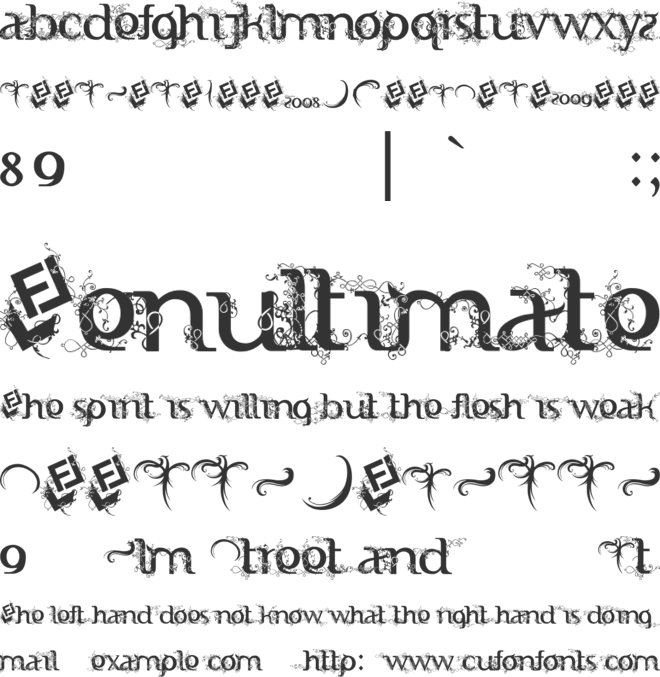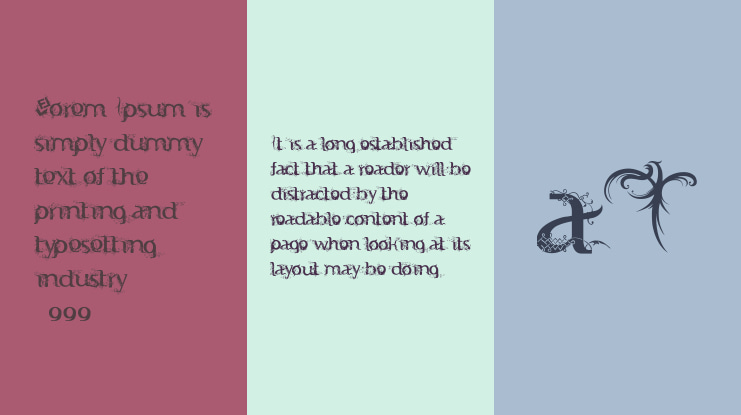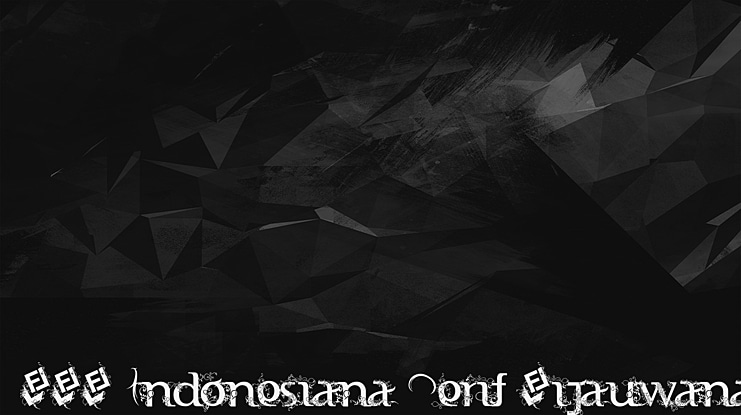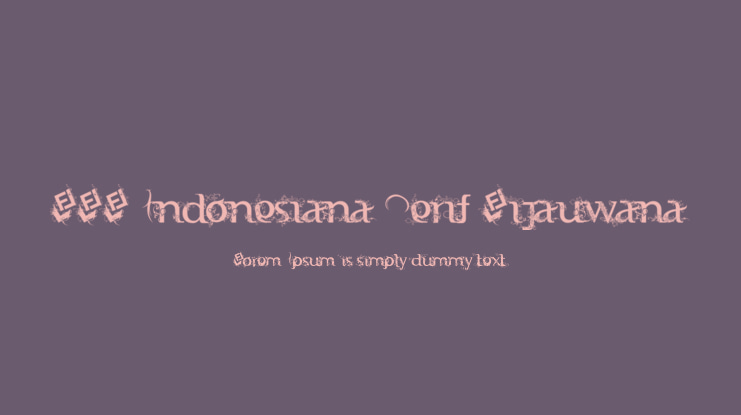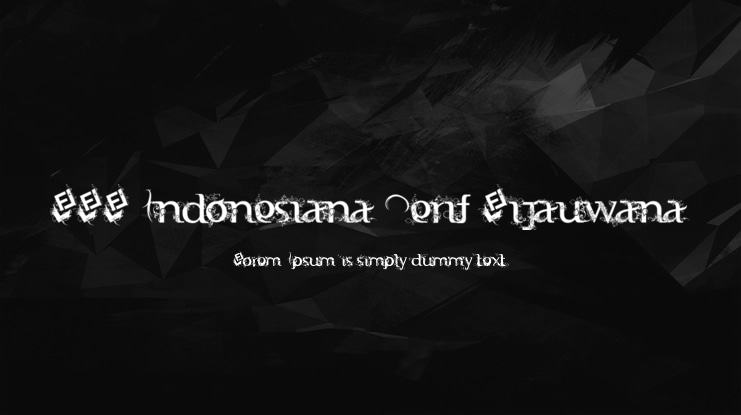
FTF Indonesiana Serif Hijauwana Font
Go Green Font Edition from Fizzetica Type Foundry - Indonesia!
-INDONESIA- Suatu kebanggaan bagi Fizz-Labz dan FTF merangkai huruf ini menjadi alfabet utuh dari a-z "lowerchase" dari logo pariwisata Visit Indonesia 2009, font ini bersifat free (free font) yang hanya boleh dipakai untuk pribadi, pendidikan dan bukan untuk kepentingan komersil.